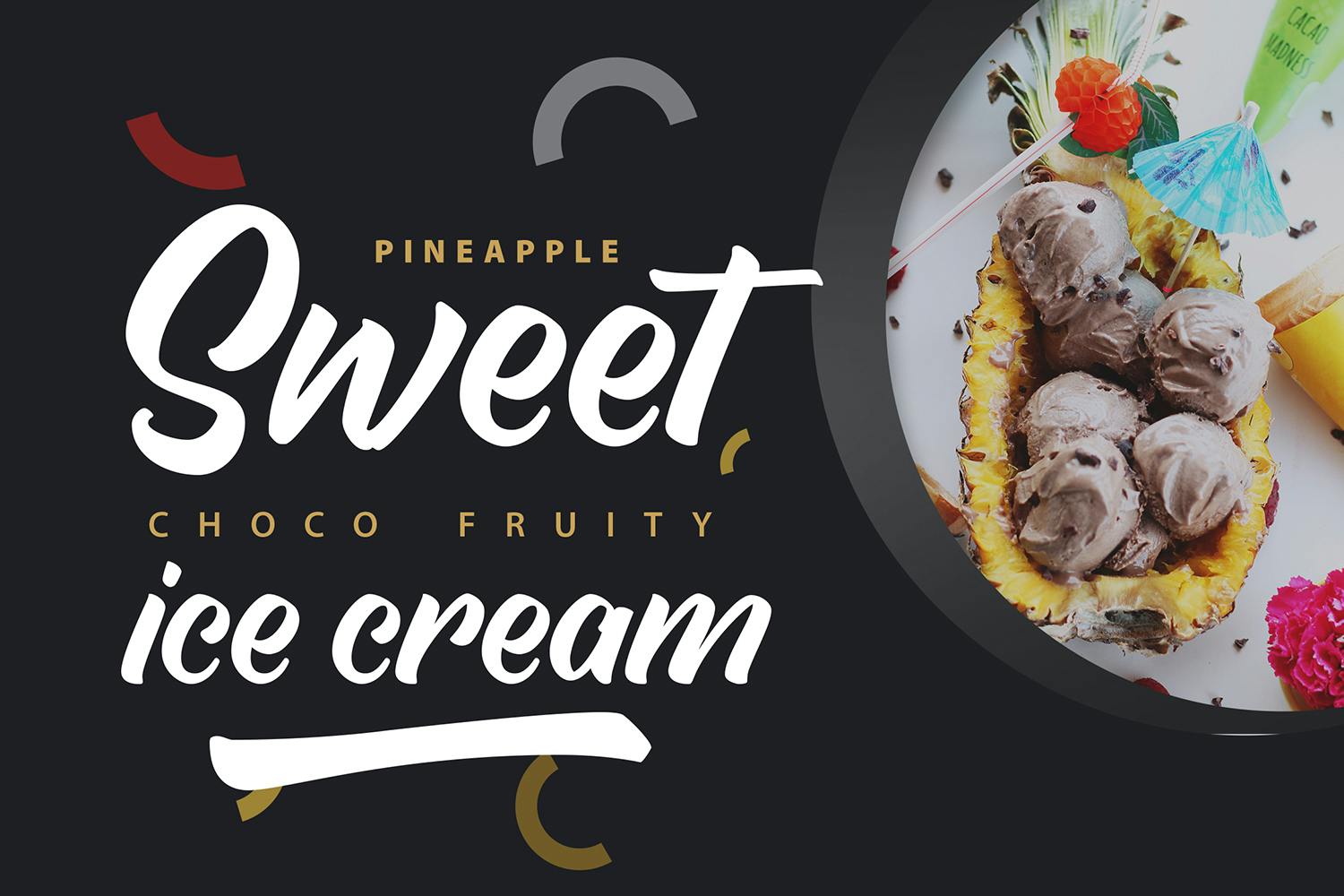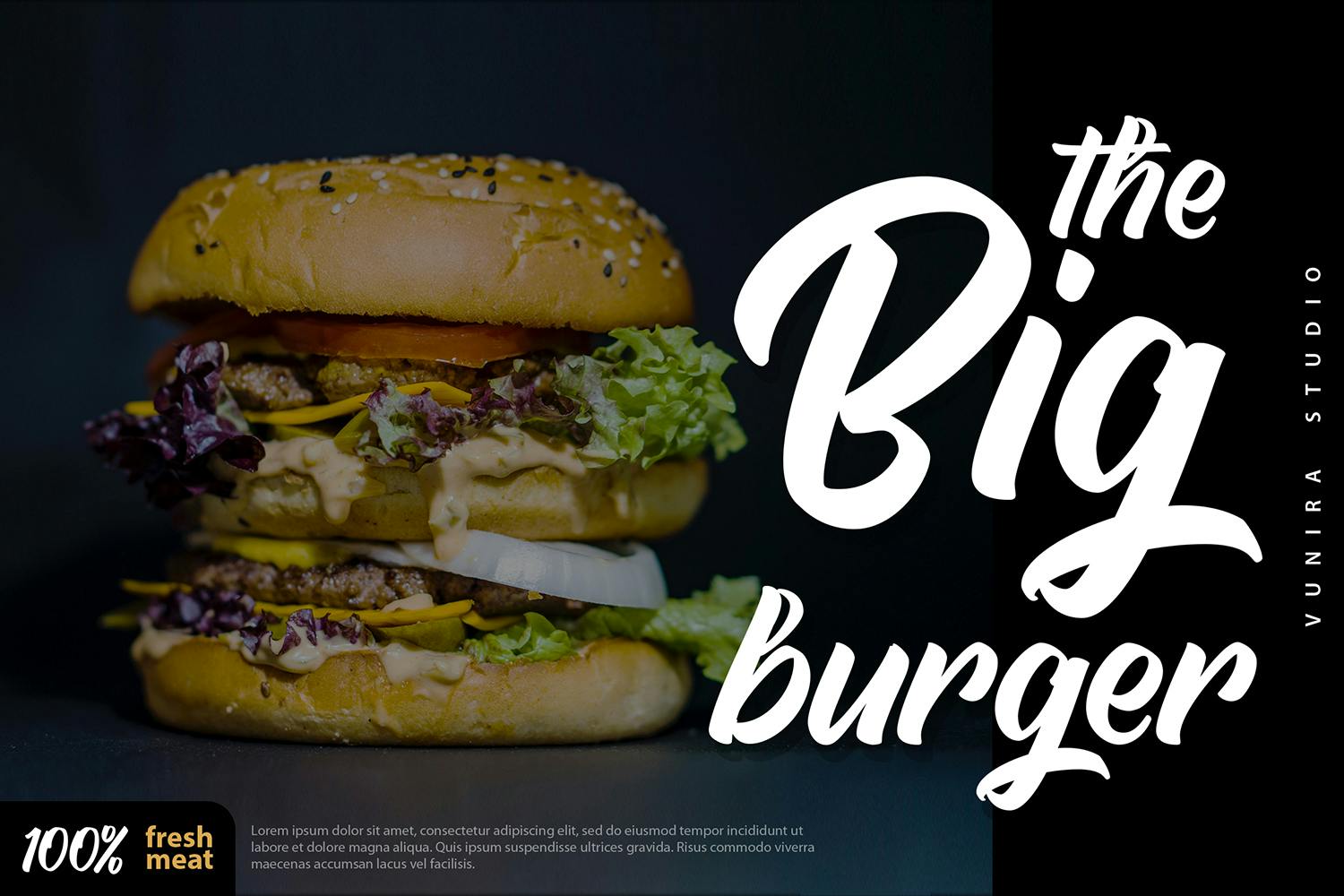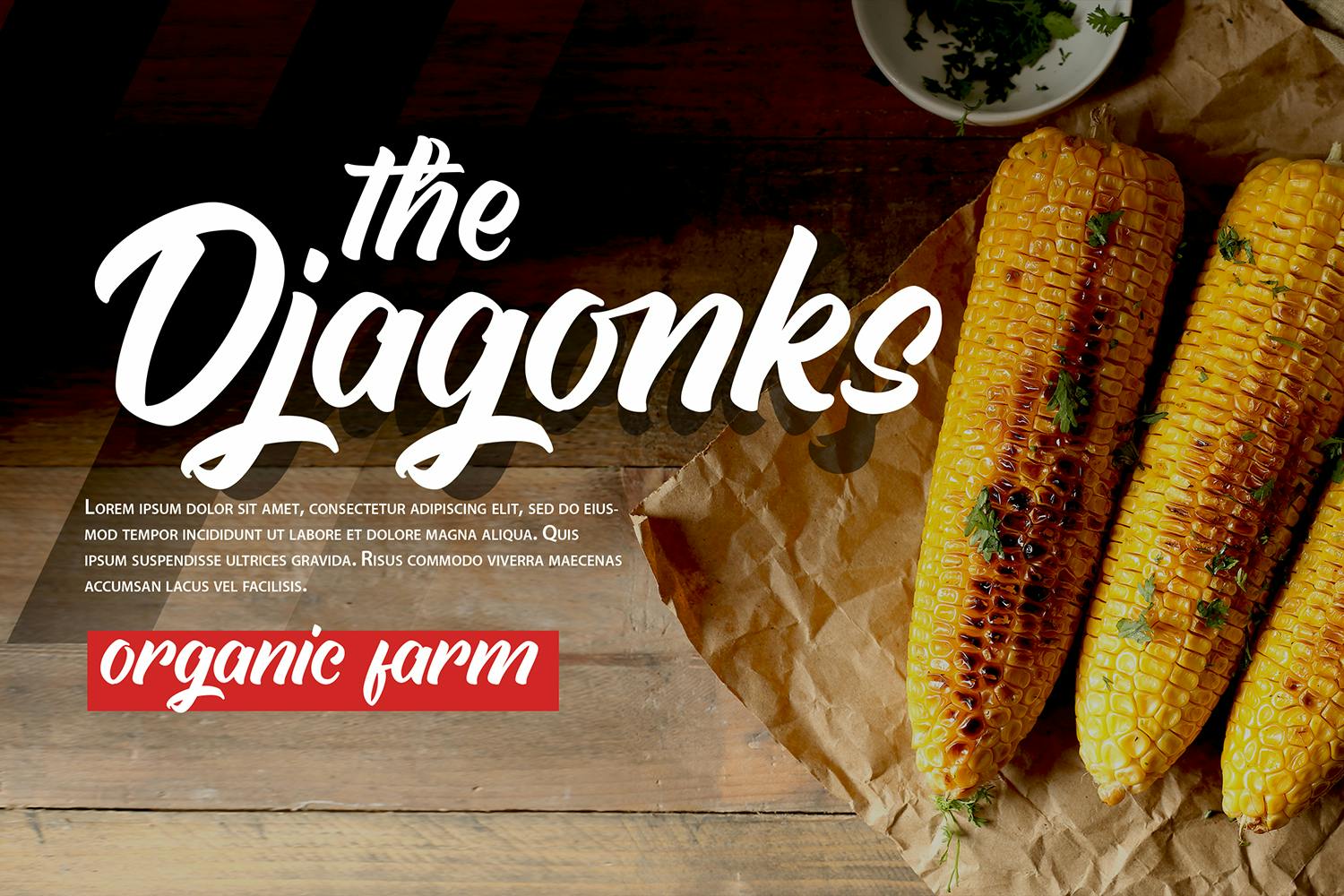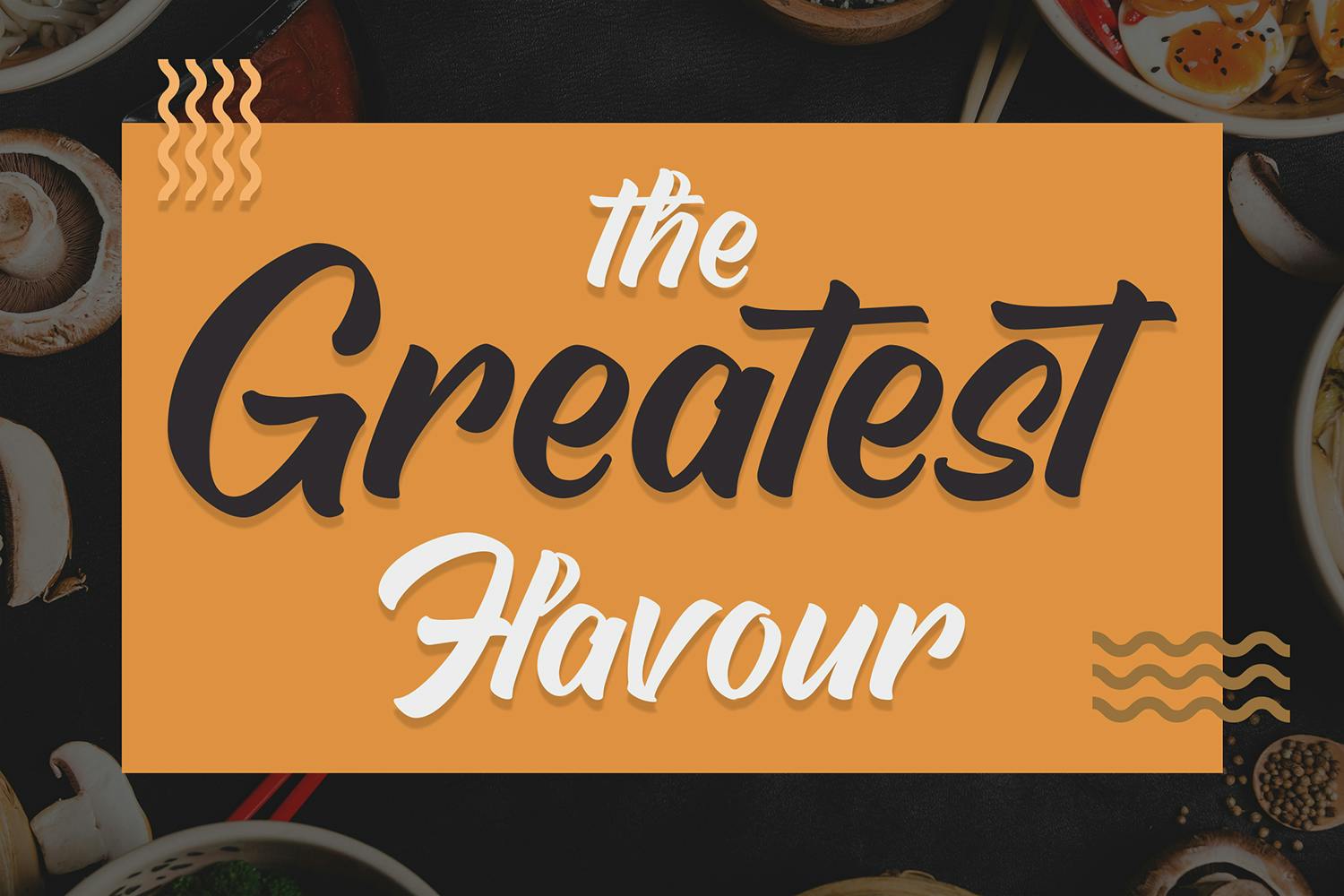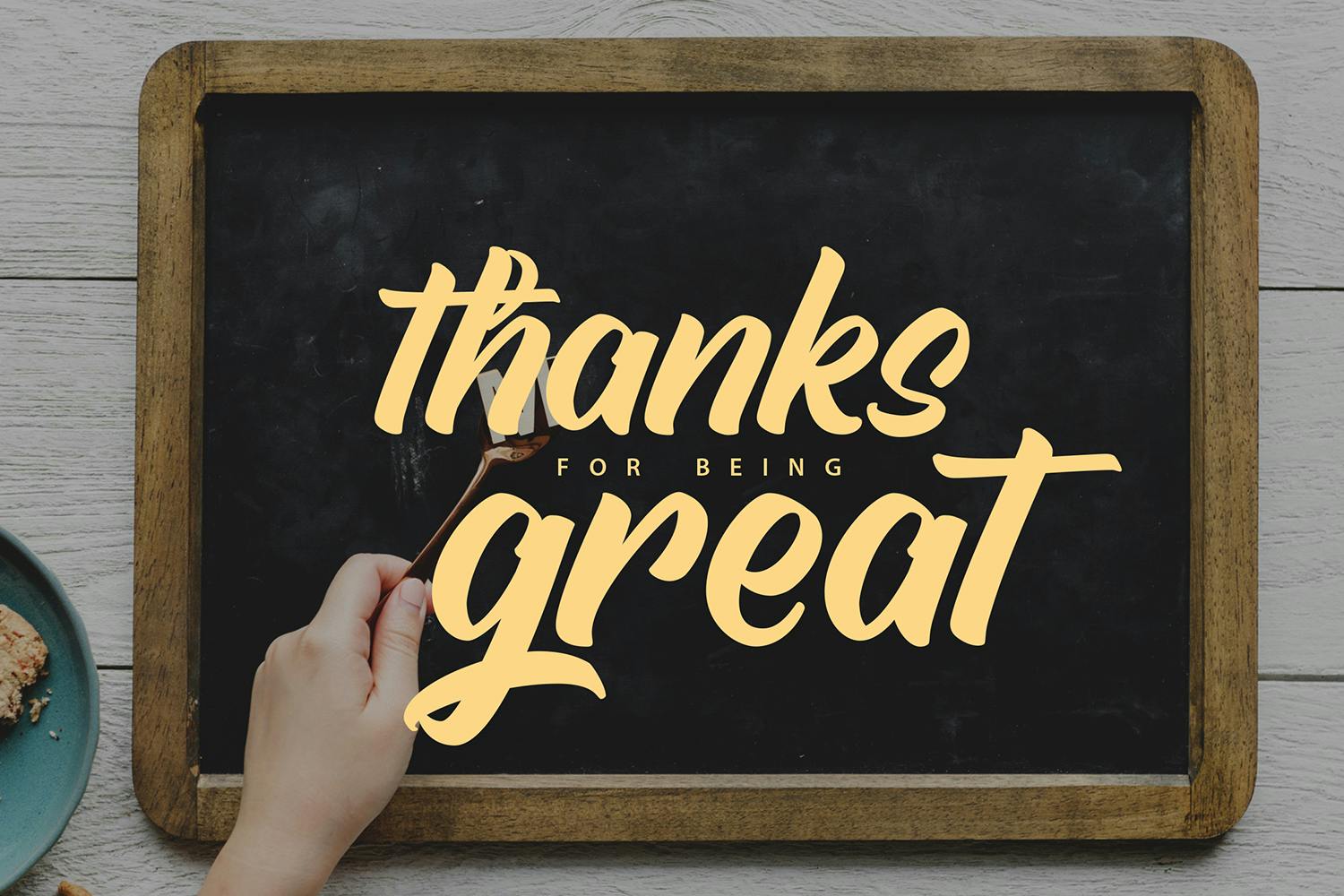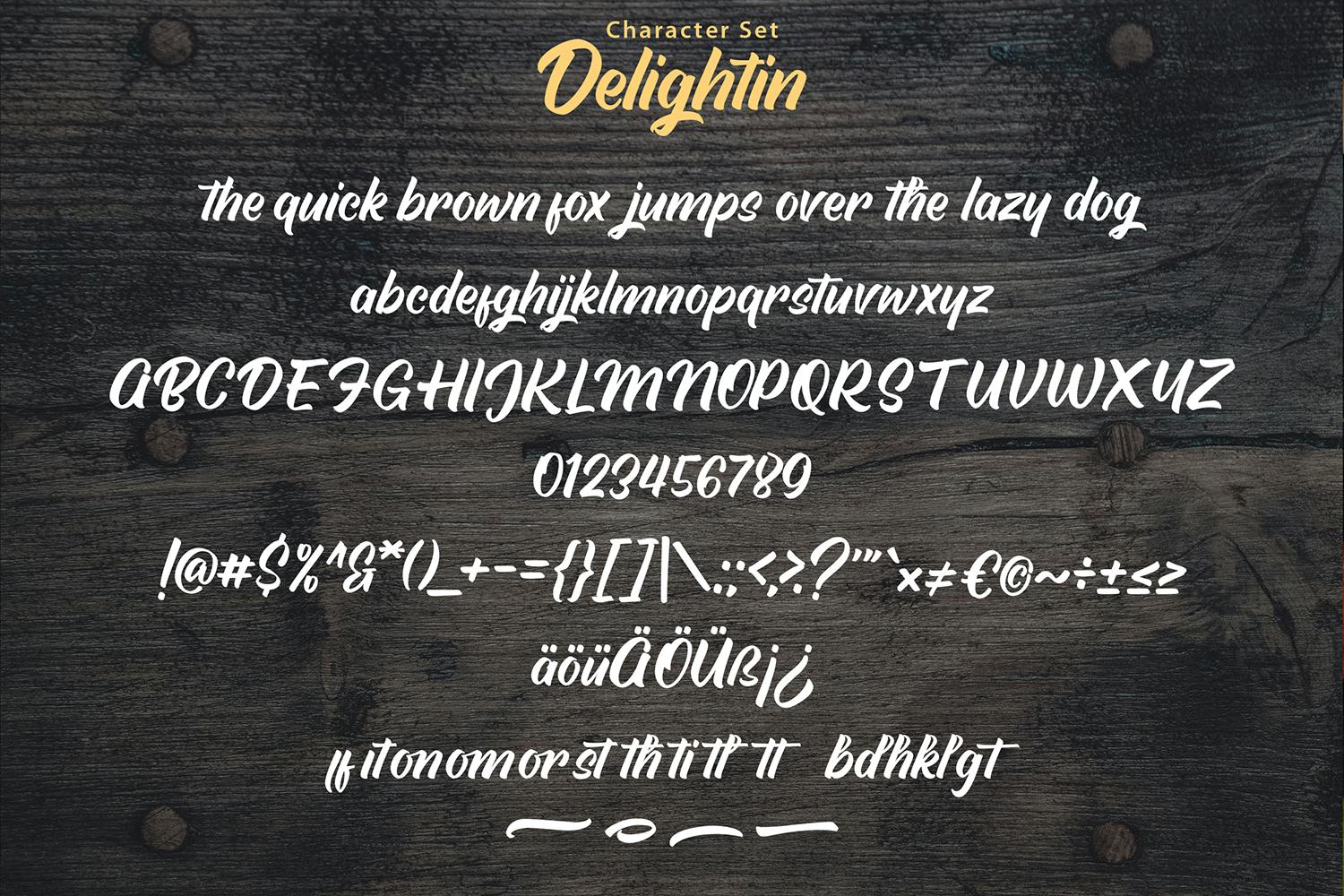
فونت Delightin | Foody Brush Lettering Script با سبک خوشنویسی، بسیار زیبا برای دعوتنامهها، کارتهای تبریک، مواد برندینگ، کارتهای ویزیت، نقلقولها، پوسترها و موارد دیگر!
کاراکترهای جایگزین به چندین ویژگی Open Type تقسیم شدهاند، مانند ستهای سبک، جایگزینهای سیاقی، SWASH و Ligature. ویژگیهای Open Type با استفاده از برنامههای حرفهای مانند Adobe Illustrator، Adobe InDesign، Adobe Photoshop، Corel Draw X و Microsoft Word قابل دسترسی هستند. این فونت دارای کدگذاری PUA (فونتهای ویژه کدگذاری شده) است، به طوری که تمام کاراکترهای جایگزین بهراحتی قابل دسترسی هستند.